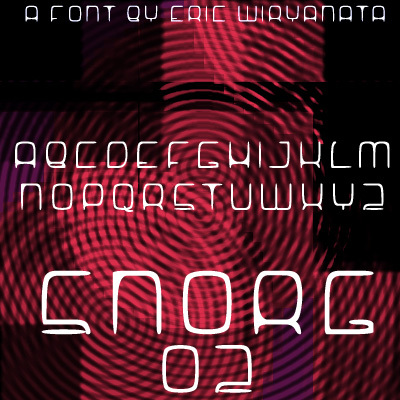
Snorg 002 di Eric Wiryanata è un font display futuristico gratuito, caratterizzato da un tratto fluido, quasi monolinea, e un approccio sottilmente sperimentale. Le maiuscole appaiono alte ed essenziali, con curve rettangolari arrotondate, angoli morbidi e alcuni tagli interni netti che impediscono alle lettere di sembrare troppo levigate o meccaniche.
È l'ideale quando serve un tocco sci-fi senza risultare freddi: titoli di locandine, loghi per videogame, grafiche per eventi tech, copertine e cartelli. L'insolito mix di cornici arrotondate e dettagli appuntiti si adatta perfettamente anche ai monogrammi e al branding essenziale, dove le lettere creano l'atmosfera da sole.